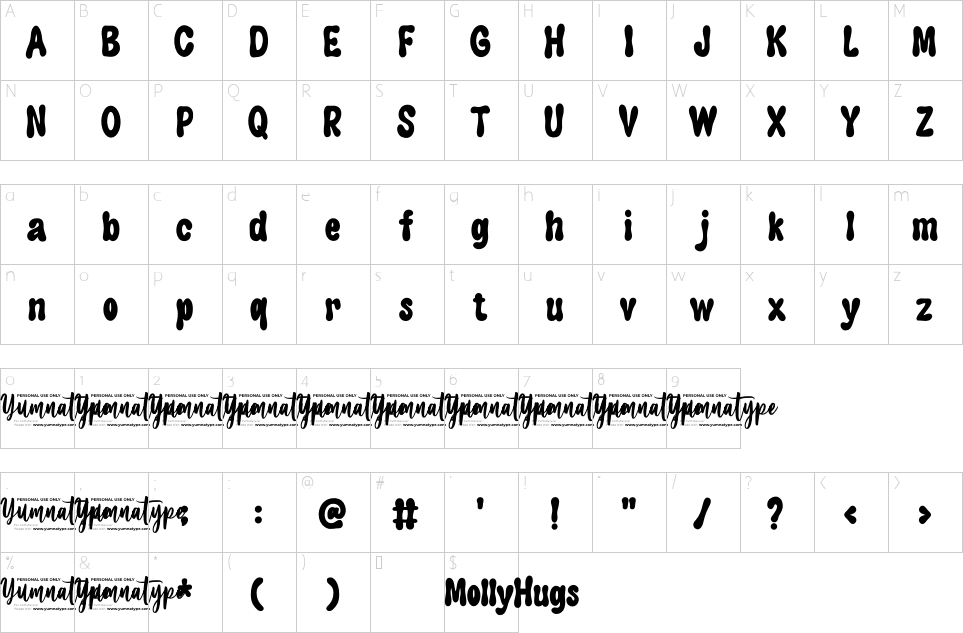
Molly Hugs é uma fonte amigável e suave que se encaixa perfeitamente em qualquer projeto que você esteja criando. Ela foi projetada por Yumna Type e está disponível gratuitamente para download tanto para Windows quanto para Mac. Sua simplicidade e delicadeza fazem dela uma opção ideal para aplicações de design gráfico, como design de logotipos, design de gráficos de texto ou até mesmo design de web. Com uma aparência agradável e suave, Molly Hugs é uma fonte perfeita para qualquer projeto que você possa estar fazendo, garantindo um toque de calma e conforto ao seu trabalho. Fique à vontade para baixar esta fonte e experimentar sua versão única.